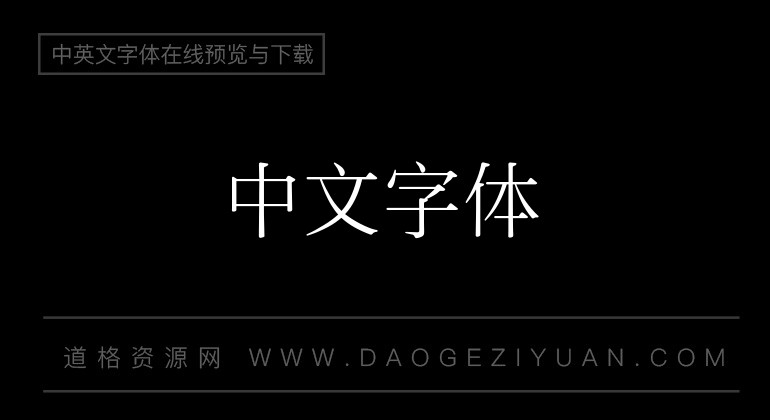
锐字云字库仿宋体GBK
锐字云字库仿宋体GBK字体是一款仿宋体GBK字体,由锐字云字库打造,具有良好的视觉效果,可以提供清晰、优雅的文本表现。锐字云字库仿宋体GBK字体采用了精细的笔画,细腻的曲线,清晰的字形,简洁的结构,从而彰显出自然、柔和、温暖的视觉效果,可以满足更多文字表达的需求,是一款优秀的仿宋体GBK字体。
锐字云字库仿宋体GBK是一款非常不错的手写艺术字体,具有很好的视觉感,适合于文化类的宣传设计、商业类品牌的广告和产品包装设计以及个性化文字排版等较多场景。